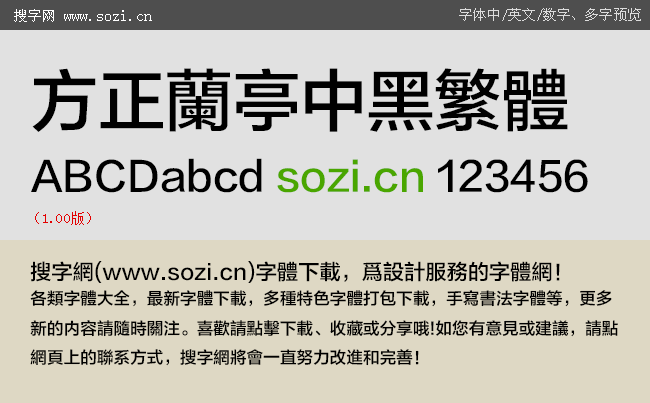
方正蘭亭中黑繁體
搜字網(wǎng)提供一款方正蘭亭中黑繁體下載,方正蘭亭中黑是一款比一般系統(tǒng)黑體粗的字體,該字體結(jié)構(gòu)優(yōu)美,識別性強,端正大方,筆鋒粗曠,整體風(fēng)格出色,適用于廣告設(shè)計、名片設(shè)計、包裝印刷、產(chǎn)品設(shè)計等應(yīng)用。